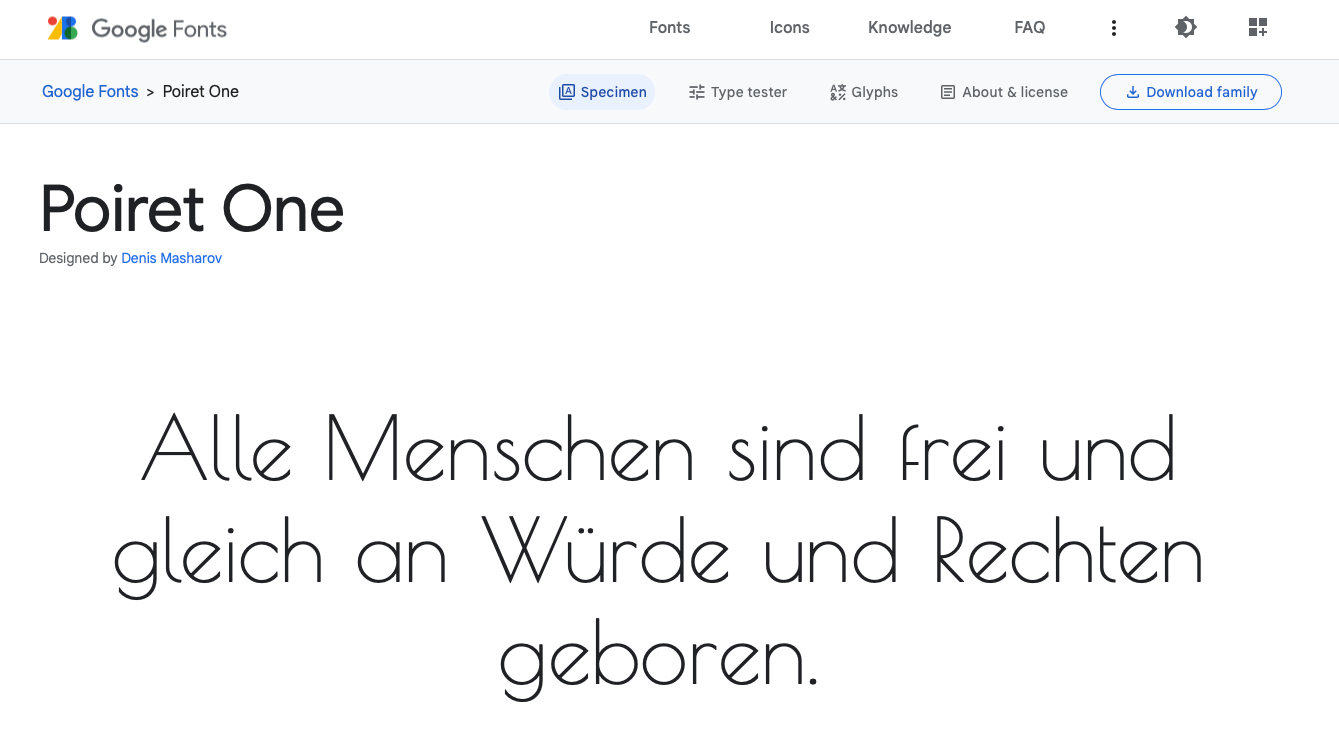
Welche Schrift passt zu "Poiret one"?
Ich habe hier einige Schriftarten, die gut als Überschrift, Titel oder kurze Beschreibungen passen:
• Chong Modern
• Bodoni Sans
• Aguila
• Flatline Sans
• Moneta
• Quiche
• Spectral (free, aber eher nicht)
Kann mir jemand weiterhelfen, ob eine von den oben genannten Schriftarten gut zu unserer aktuellen Schrift für Textabsätze „Poiret one” passt? Grundsätzlich würden wir diese gerne behalten, wären aber auch bereit eine andere dazu zu nehmen.
Ohne zu wissen, in welcher Umgebung/Branche wir hier uns bewegen: Ich möchte von der Poiret One als Fließtextschrift abraten. Viel zu ermüdend, sie auf Dauer zu lesen. Nimm bitte etwas Unspektakuläreres, das man auch in längeren Passagen lesen kann.
Also Du solltest echt etwas Kontext nachliefern, denn bisher scheint es, als ob Du eine Auszeichnungsschrift, die teilweise als Textschrift genutzt werden soll, zu einer als Textschrift verwendeten Auszeichnungsschrift suchst?
Das kann vielleicht in einem hippen enddesignten Bildband mit homöopathischen Textanteil funktionieren oder für Parfumwerbung, aber dann wird die Luft für das Vorhaben schon recht dünn.
Danke für die Hinweise. Es geht um die Branche Schmuck.
Die Auszeichnungsschrift darf gerne hochwertig und extravagant aussehen wie etwa Chong Modern. Dazu sollte die Grundschrift eher schlicht und einfach sein, um einen guten Kontrast zu erzielen. Ich bin auch kein Fan von Poiret One, also die kann gerne als Grundschrift ersetzt werden.
Da geht so unendlich viel. Da müsste man eigentlich erstmal ein paar tiefergehende Analysen durchführen.
Hier mal zwei Paare aus dem Bauch raus:
mit dieser für den Fließtext:
oder
mit